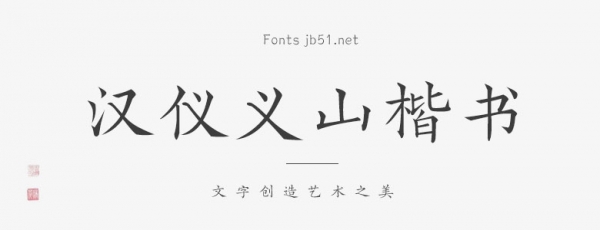
漢儀義山楷書是一款賞心悅目、百看不厭的手寫風(fēng)格字體,字體線條粗細(xì)適中,筆畫隨性,結(jié)構(gòu)肆意灑脫,具有很好的視覺感,適合于文化類的宣傳設(shè)計(jì)、商業(yè)類品牌的廣告和產(chǎn)品包裝設(shè)計(jì)以及個(gè)性化文字排版等較多場(chǎng)景。